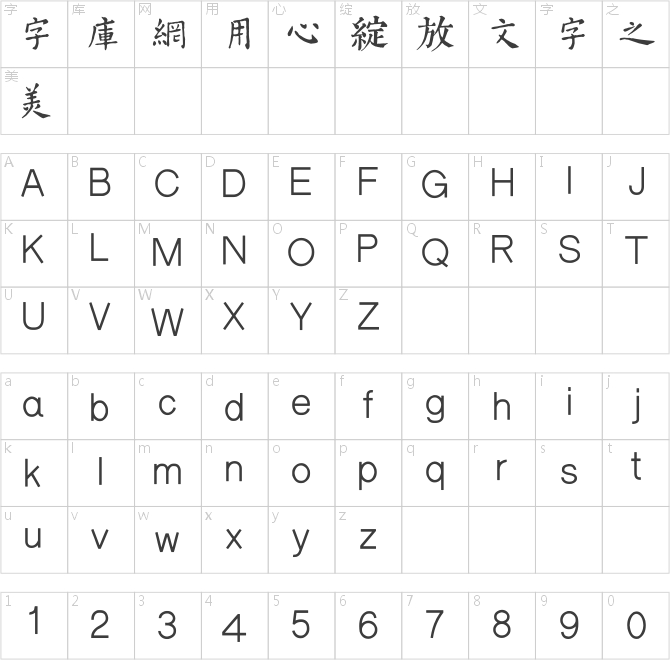
字體名稱: 邯鄲歐陽詢千字
作者版權: 韓紹杰
邯鄲歐陽詢千字文
注:本字庫為古籍千字文復刻書法小字庫,字符數量為1000余字,如有特殊需求,可以聯系邯鄲字庫韓紹杰為您訂制,也可以聯系本站客服為您轉答!
歐陽詢(557年—641年),字信本,漢族,唐朝潭州臨湘(今湖南長沙)人,唐朝著名書法家、官員,楷書四大家之一。南梁征南大將軍歐陽頠之孫,南陳左衛將軍歐陽紇之子,南朝梁太平二年(公元557年)出生于衡州(今湖南衡陽),祖籍潭州臨湘(今湖南長沙)。 歐陽詢與同代的虞世南、褚遂良、薛稷三位并稱初唐四大家。因其子歐陽通亦通善書法,故其又稱“大歐”。 歐陽詢與虞世南俱以書法馳名初唐,并稱“歐虞”,后人以其書于平正中見險絕,最便于初學者,號為“歐體”。
邯鄲歐陽詢千字文字體字庫是一款讓人賞心悅目、百看不厭的中文字體,適合各類廣告和產品包裝設計應用,字體大小6.56MB,格式為ttf字體,上傳用戶是邯鄲字庫,作者/版權方為韓紹杰